设计师在进行设计时,字体运用的是否得当是直接决定作品的成败的。选择一款合适的字体可以准确的表达出作品的蕴涵的信息展现作品的美感。但是展示出的 字体图片 琳琅满目,在选择上着实是有些困难。其实根据作品的风格“对症下药”就容易许多,今天要给大家推荐的一款字体风格比较可爱、有趣。一起来看看吧~
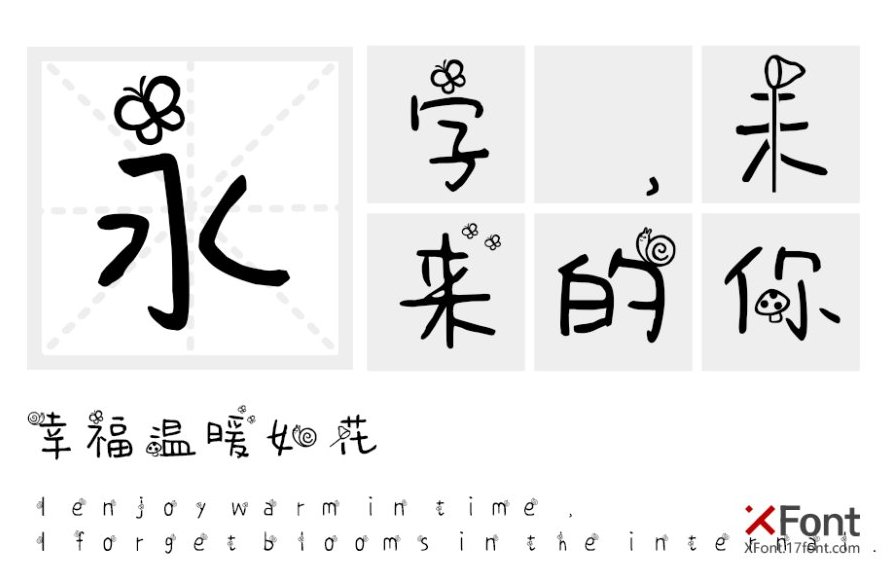
维尼历险记:这款字体使人仿佛进入了童话的世界,在这个世界里和暖的阳光照耀着青青草地,微风浮起,花香扑面,蝴蝶飞舞,鸟儿高歌,好生惬意。字体的线条简单,转折圆润,点、横处把线条变为图案增添了童趣与活力感。用于 母婴设计、广告设计、温馨活动标题都非常合适。
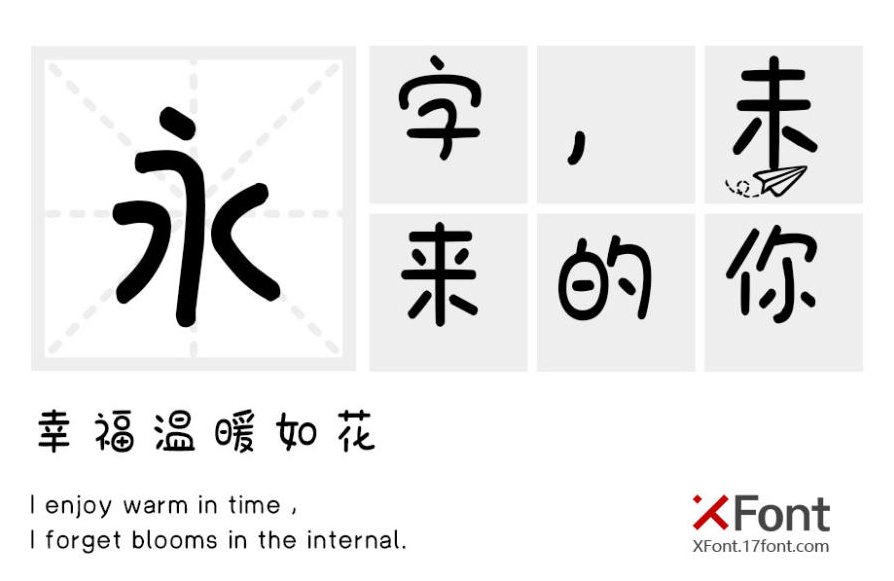
青春的天空:这款字体的线条底部衔接着纸飞机,寓意是传递希望和梦想。文字结构灵活精巧,笔画圆钝,童稚十足。风格鲜明、清新萌动。用于 儿童类logo设计会起到画龙点睛的效果,在产品包装设计、社交网络等方面使用都相得益彰。
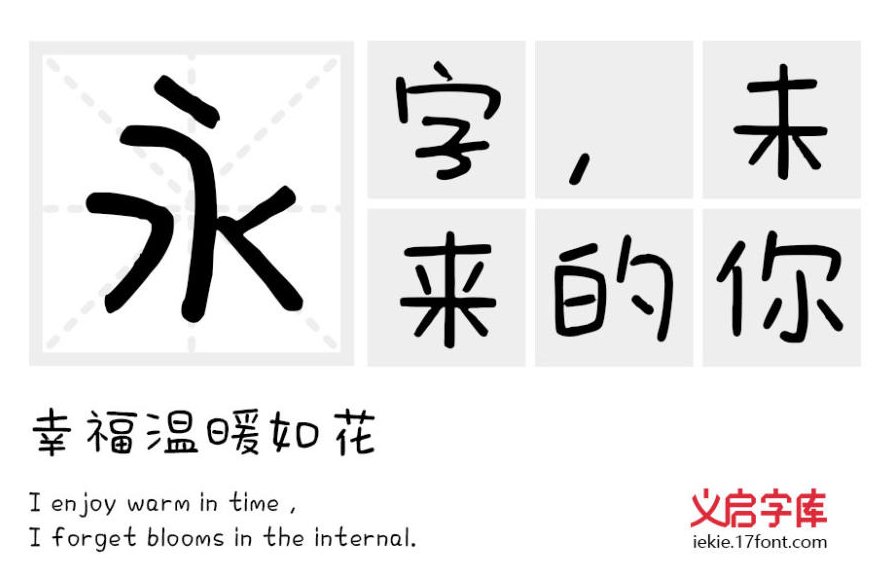
这款 “萌鼠贺新年” ,由单线条组成没有与上两款字体一样的图案装饰,主要以饱满带有圆体的卡通形式呈现字体结构。字形和结构重心一致,字体识别度高,易于阅读。字体个性活泼可爱、伶俐乖巧。在儿童类书刊、包装设计 、广告设计都非常合适。